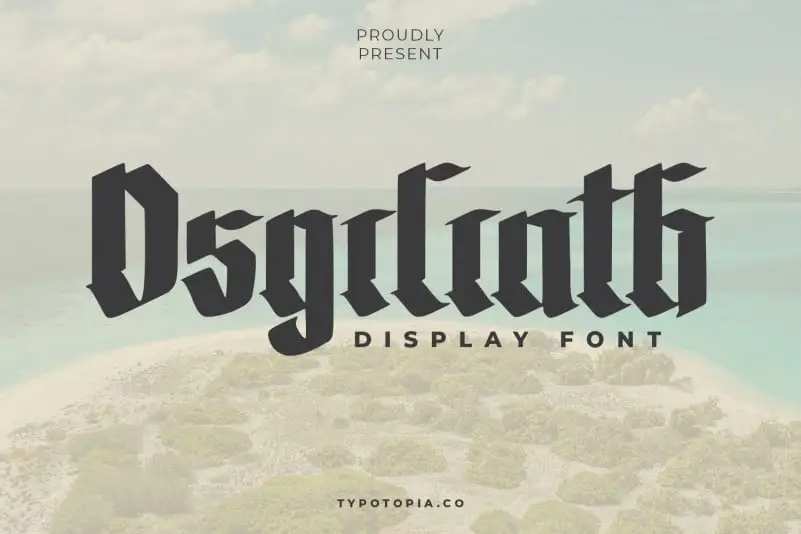
The Osgiliath Display Font
A fonte ‘The Osgiliath Display Font’ traz uma experiência única e intrigante para seus projetos de design. Esta fonte é perfeitamente adaptada para uma vasta gama de aplicabilidades, desde logotipos até etiquetas, passando por cartões de presente ou embalagens de produto. Seja qual seja seu próximo projeto criativo, a ‘The Osgiliath Display Font’ certamente o ajudará a destacar-se. Com sua personalidade única e suas formas arredondadas, esta fonte será uma escolha inteligente tanto para designers de logotipos quanto para aqueles que desejam imprimir frases memoráveis ou criar cartões de visita elegantes. Além disso, pode ser usada em qualquer aplicação visual que você possa imaginar – seja ela um adesivo de camiseta ou uma impressão impressa no painel de uma empresa. Sua complexidade e originalidade garantem que a ‘The Osgiliath Display Font’ seja uma opção confiável para todos os projetos de design, oferecendo um toque distintivo sem comprometer sua legibilidade.